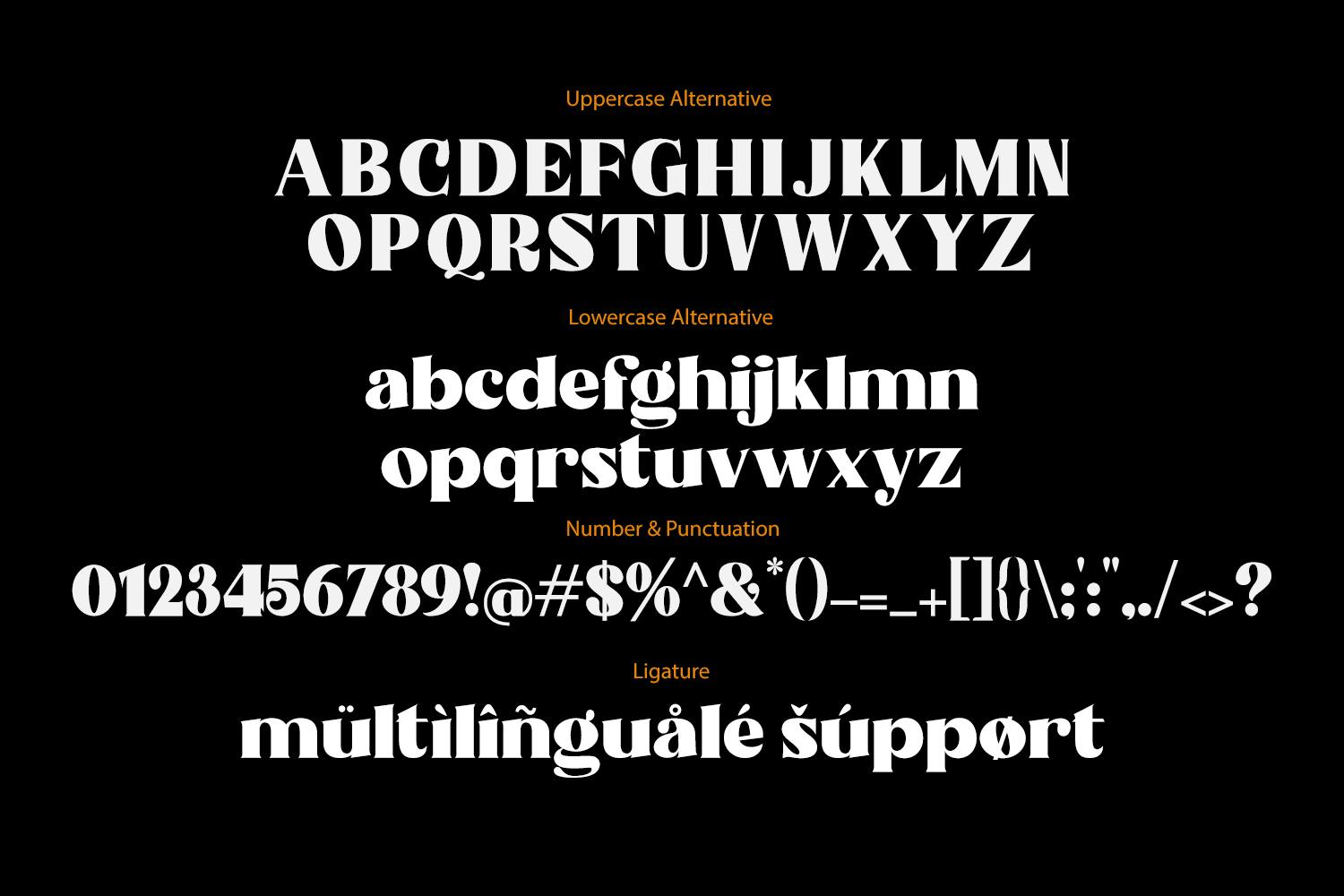
Prima Luxury Typeface
فونت پریما لوکس با طراحی خاص و کاراکترهای زیبا، گزینه‌ای مناسب برای پروژه‌های شماست.
با افتخار فونت پریما لوکس را معرفی می‌کنیم.
پریما یک فونت لوکس است که شامل لیگاتورها و گزینه‌های متنوع برای هر کاراکتر می‌باشد و در دو نسخه صاف و خشن ارائه شده است! طراحی‌های شیک و متنوع این فونت آن را برای هر نوع پروژه طراحی مناسب می‌سازد.
ویژگی‌ها
• حروف بزرگ
• حروف کوچک
• اعداد و نمادها
• گلیف‌های بین‌المللی
• گزینه‌های جایگزین
• لیگاتورها